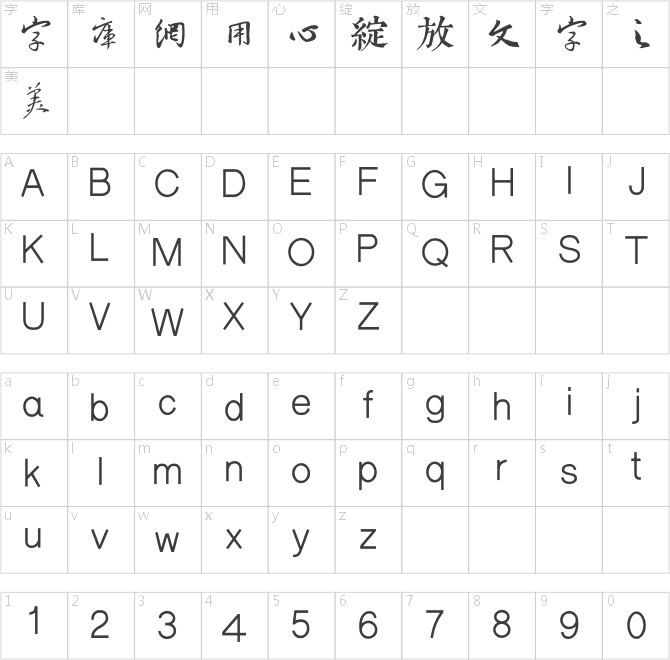
邯鄲
注:本字庫(kù)為古籍千字文復(fù)刻書法小字庫(kù),字符數(shù)量為1000余字,如有特殊需求,可以聯(lián)系邯鄲字庫(kù)韓紹杰為您訂制,也可以聯(lián)系本站客服為您轉(zhuǎn)答!王羲之(303—361,一說(shuō)321—379),字逸少,東晉時(shí)期書法家,有“書圣”之稱?,樼鹋R沂(今山東臨沂)人,南渡后居會(huì)稽山陰(今浙江紹興),晚年隱居剡縣金庭。 歷任秘書郞、寧遠(yuǎn)將軍、江州刺史,后為會(huì)稽內(nèi)史,領(lǐng)右將軍。其書法兼善隸、草、楷、行各體,精研體勢(shì),心摹手追,廣采眾長(zhǎng),備精諸體,冶于一爐,擺脫了漢魏筆風(fēng),自成一家,影響深遠(yuǎn)。風(fēng)格平和自然,筆勢(shì)委婉含蓄,遒美健秀。李志敏評(píng)價(jià):“王羲之的書法既表現(xiàn)以老莊哲學(xué)為基礎(chǔ)的簡(jiǎn)淡玄遠(yuǎn),又表現(xiàn)以儒家的中庸之道為基礎(chǔ)的沖和?!贝碜鳌短m亭序》被譽(yù)為“天下第一行書”。在書法史上,他與其子王獻(xiàn)之合稱為“二王”。